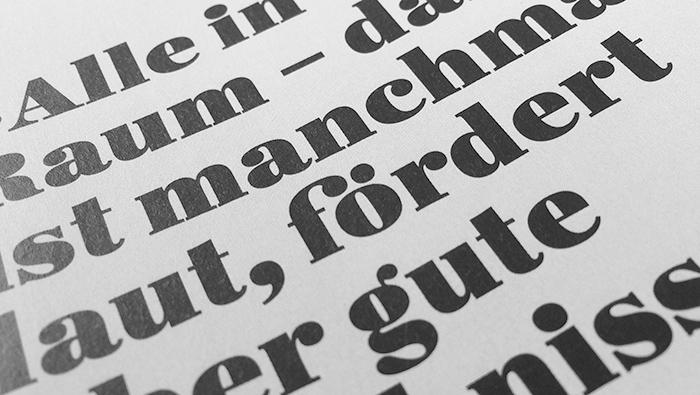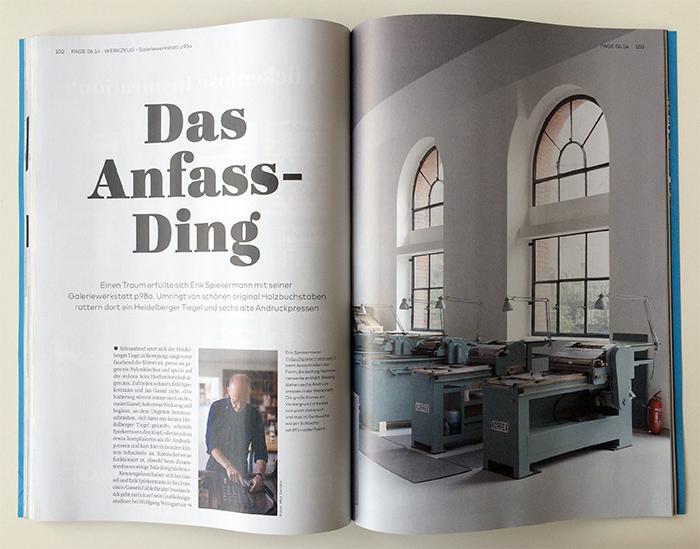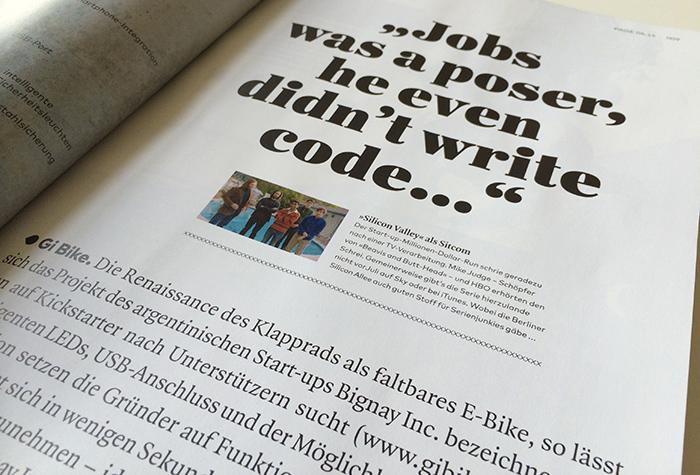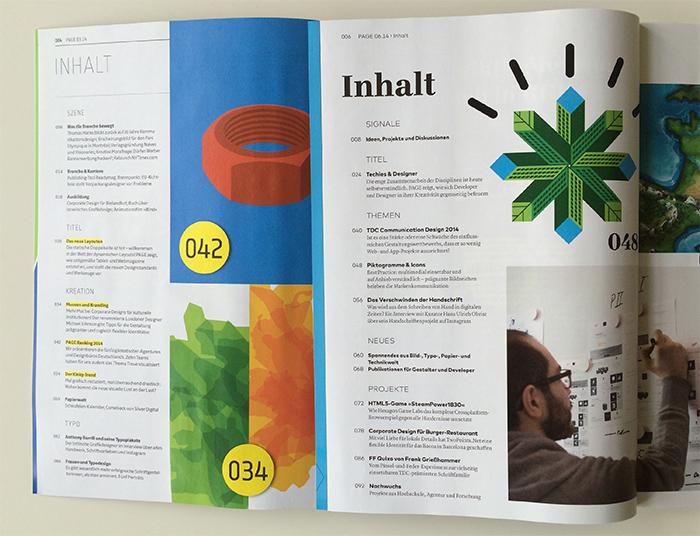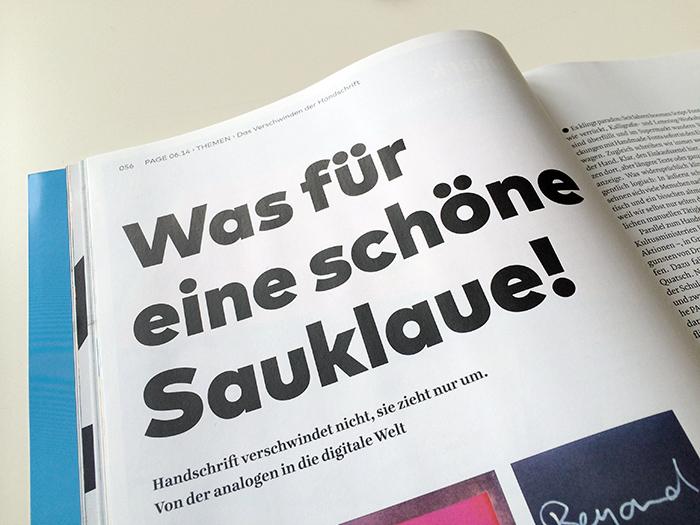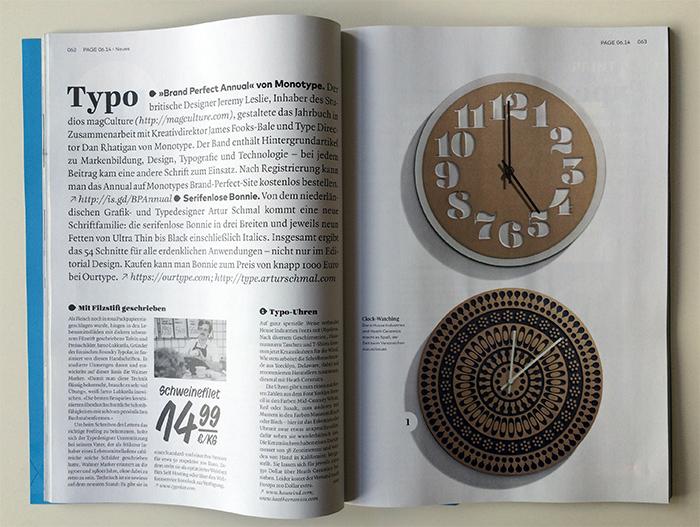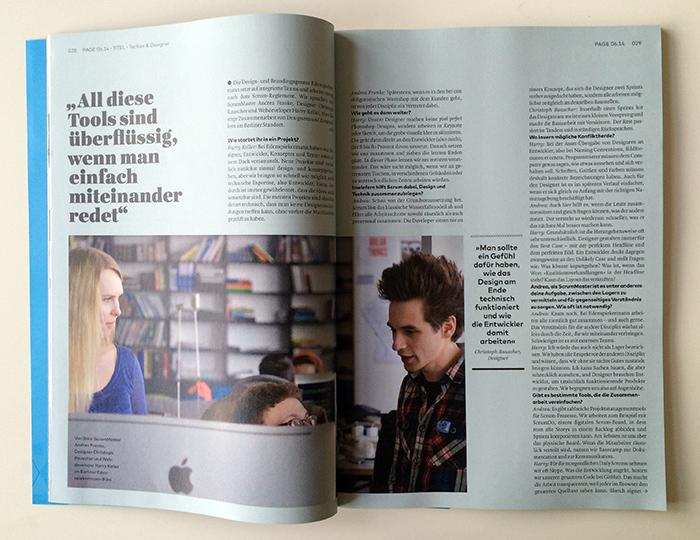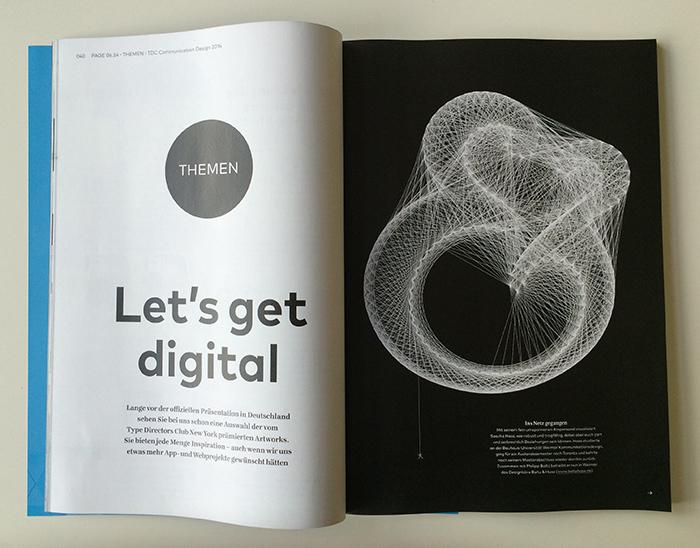
Vor 5 Jahren stellte der Ebner Verlag seiner etablierten PAGE eine Schwester-Zeitschrift zur Seite, die sich speziell dem Design und der Entwicklung bei den neuen interaktiven Medien verschrieben hatte. Nun wird dieses »WEAVE« genannte Magazin wieder eingestellt und fusioniert mit der PAGE, die fortan mit mehr Seiten und entsprechend neuen Rubriken erscheint. Im Zuge dieser Zusammenlegung hat sich die PAGE ein Redesign verpasst, das insbesondere die Typografie betrifft.
Statt der technisch-nüchternen PTL Notes und PTL Magpage kommen fortan gleich drei recht unterschiedliche Schriften zum Einsatz: die Ingeborg und die FF Mark für Überschriften, Zitate, Bildunterschriften etc. sowie die FF Quadraat als neue Fließtextschrift. Das Layout wurde nicht grundlegend verändert, erscheint aber nun deutlich luftiger und betont die Typografie als Träger der visuellen Identität des Magazins. Für mich ein gelungener evolutionärer Schritt.
Inhaltsverzeichnis der alten (links) und neuen PAGE (rechts)